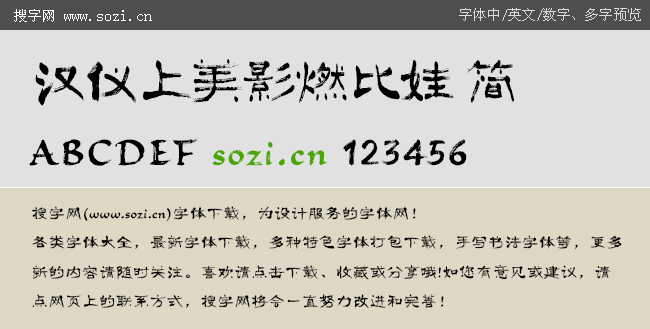
漢儀上美影燃比娃 簡(jiǎn)
搜字網(wǎng)給大家提供一款漢儀上美影燃比娃 簡(jiǎn)中文字體下載,漢儀上美影燃比娃字體是一款手寫風(fēng)格的毛筆字體,字體筆畫隨性大方,結(jié)構(gòu)肆意灑脫,整體效果非常不錯(cuò)。適用于畫冊(cè)設(shè)計(jì)、海報(bào)設(shè)計(jì)、包裝設(shè)計(jì)等場(chǎng)合使用。(本字體為個(gè)人非商用版,如需要商用請(qǐng)聯(lián)系漢儀公司購(gòu)買版權(quán))